Indietro WhatsApp A poco a poco come una delle app di messaggistica più popolari in tutto il mondo. Con oltre 1.5 miliardi di abbonati, l'app di chat è il modo preferito per interagire con amici, professionisti e persino inviare e condividere file multimediali e file.
È passato un po' di tempo prima che abbia aggiunto un'app WhatsApp Una funzione per cambiare il formato del testo delle conversazioni per rendere le tue chat più interessanti ed estetiche.
Conosci già le tecniche per grassetto, corsivo e barrato tra i tuoi messaggi di testo. Ma sapevi anche che puoi cambiare il tuo noioso font di testo in una macchina da scrivere?
Sì, non è un segreto ed è possibile cambiare il carattere per rendere le tue chat più estetiche. La macchina da scrivere sempre preferita rappresenta tutto il successo su ogni piattaforma social che lo consente.
chat È la cosa più importante da fare su WhatsApp e ci sono alcuni modi per personalizzarla. Uno di questi è la possibilità di cambiare lo stile e il formato del testo. Non solo puoi digitare il testo in grassetto o corsivo nelle tue chat, puoi anche cambiare lo stile del carattere all'interno delle immagini che invii. Quindi, la prossima volta che stai pensando di condividere un'immagine o vuoi enfatizzare una determinata parola, segui questi passaggi per differenziarti dai normali utenti di WhatsApp. Vediamo come puoi farlo.
1. Modifica il testo nelle tue conversazioni
corsivo
Basta aprire una chat privata o di gruppo e scrivere il messaggio. Quindi, siamo sulla stessa pagina, usiamo la frase "Ciao, come stai?" come modulo di messaggio condiviso. Per scrivere in corsivo tutto ciò che devi fare è usare un trattino basso su entrambi i lati del testo.
Ad esempio, digita _Ciao, come stai?_ واضغط ج Spedire.
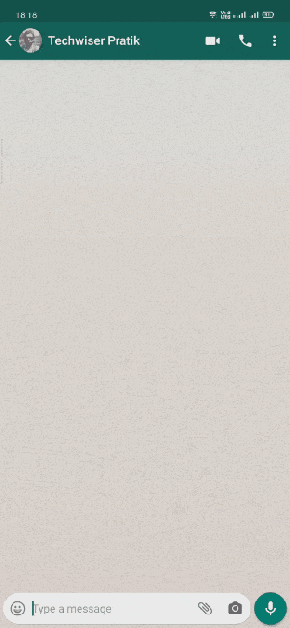
carattere in grassetto
Per convertire il testo normale in grassetto, metti semplicemente un asterisco su entrambi i lati del testo.
Ad esempio, digita *Ciao, come stai?* واضغط ج Spedire.
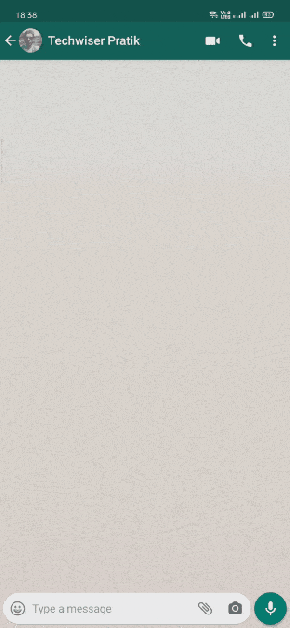
barrato
Un altro modo è utilizzare uno stile barrato nel testo. Per fare ciò, devi mettere una tilde ~ su entrambi i lati del testo.
Ad esempio, digita ~Ciao, come stai?~ ثم اضغط 中 Spedire.
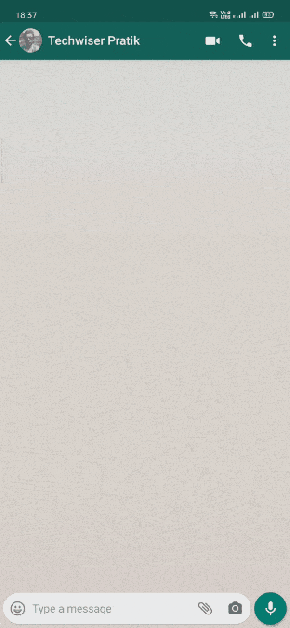
testo monospazio
Se sei un programmatore, devi avere familiarità con il carattere a spaziatura fissa. Puoi usare questo stile di carattere anche in WhatsApp. Per applicare questo stile, usa `` su entrambi i lati del testo.
Ad esempio, digita “`Ciao, come stai?”`` واضغط ج Spedire.
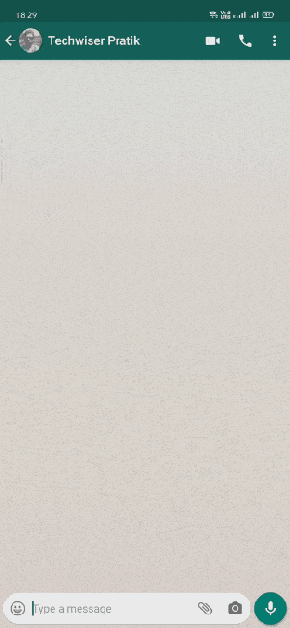
In alternativa, puoi selezionare il testo che desideri modificare e scegliere tra le opzioni sopra descritte nel menu espanso. Non utilizzo questa impostazione, tuttavia, questo metodo potrebbe essere più semplice per molte persone.
2. Modifica il testo nelle foto
Preparare Stato e immagini di WhatsApp Un buon modo per dire ai tuoi amici cosa farai. Puoi aggiungere testo all'immagine e cambiare anche il colore, ma non esiste un'opzione ovvia per cambiare il carattere, ma puoi comunque farlo. Vediamo come farlo.
Puoi fare clic su una nuova foto o aprire una foto dalla tua galleria e scegliere "T" nell'angolo in alto a destra. Usiamo la stessa forma di testo dell'esempio precedente - "Ciao, come stai?"".
Quindi tocca e fai scorrere il dito dalla sezione del selettore dei colori a sinistra dello schermo. Questo ti mostrerà un'anteprima di diversi tipi di carattere, tra cui puoi scegliere. Quando ottieni il motivo desiderato, solleva il dito.
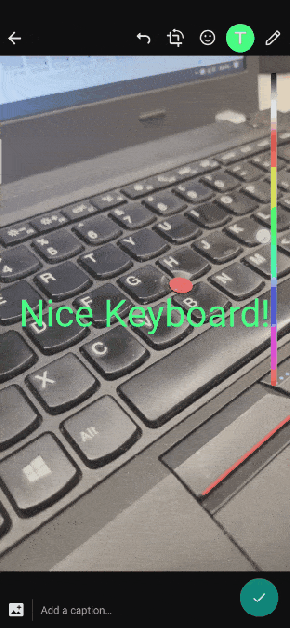
Nota che non ci sono molte opzioni di testo ma potrebbero essere sufficienti, però. Se hai ancora bisogno di più stili di carattere, continua a leggere.
3. Copia il testo dai siti Web per cambiare i caratteri
Esistono molti siti Web in cui puoi scrivere in testo normale e avere lo stile del carattere che desideri. So che è un processo lungo rispetto alle altre opzioni di cui abbiamo parlato, ma comunque, se stai cercando uno stile specifico o se conosci il nome dello stile del carattere che stai chiedendo, questo è l'unico modo andare.
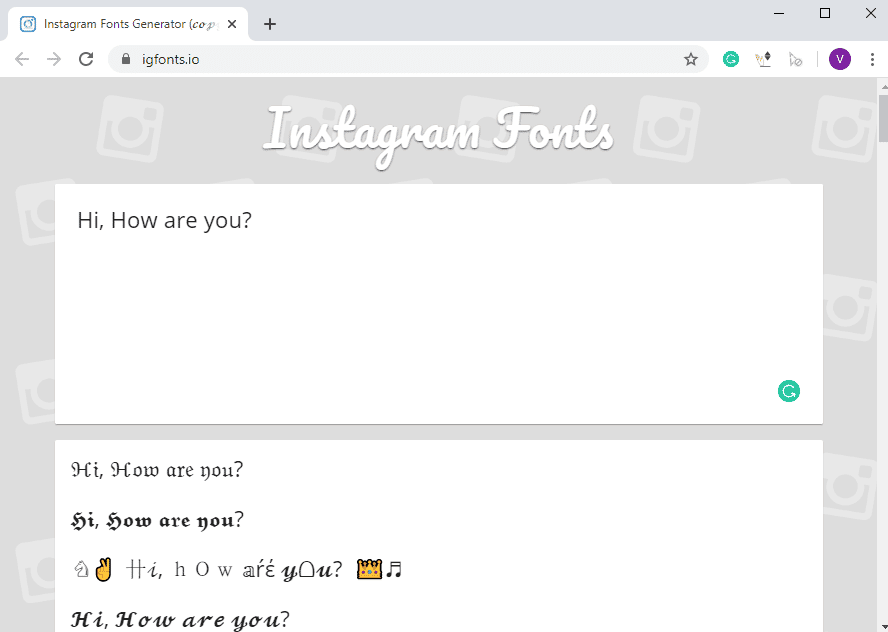
Puoi cercare siti di modifica dei caratteri online o utilizzare marmellata di lingo أو igfont per l'esperienza. Questo è un ottimo metodo se stai usando Web WhatsApp. Tuttavia, è necessario digitare il testo e quindi copiarlo/incollarlo nella chat.
4. Applicazioni di terzi
Esistono molte applicazioni che ti consentono di cambiare il carattere e aggiungere stili diversi. In questo modo non sei limitato alle scelte all'interno di WhatsApp. Eccone alcuni che puoi provare.
Copia ovunque, testo elegante È un'applicazione con molti stili tra cui puoi scegliere. La parte migliore è che puoi scrivere il testo all'interno dell'app e condividerlo direttamente su WhatsApp.
Include Caratteri per WhatsApp Anche su molti font. Ciò che lo rende diverso dalle altre app è che ha anche un lungo elenco di altri tag e icone. Ricordi le lunghe lettere di Orkut fatte di testo normale? Questo è esattamente quello che troverai.ツ.